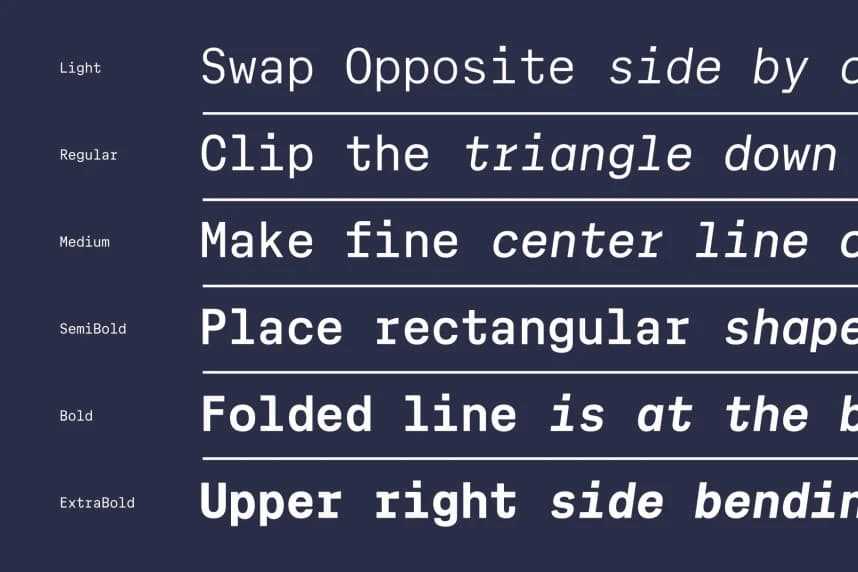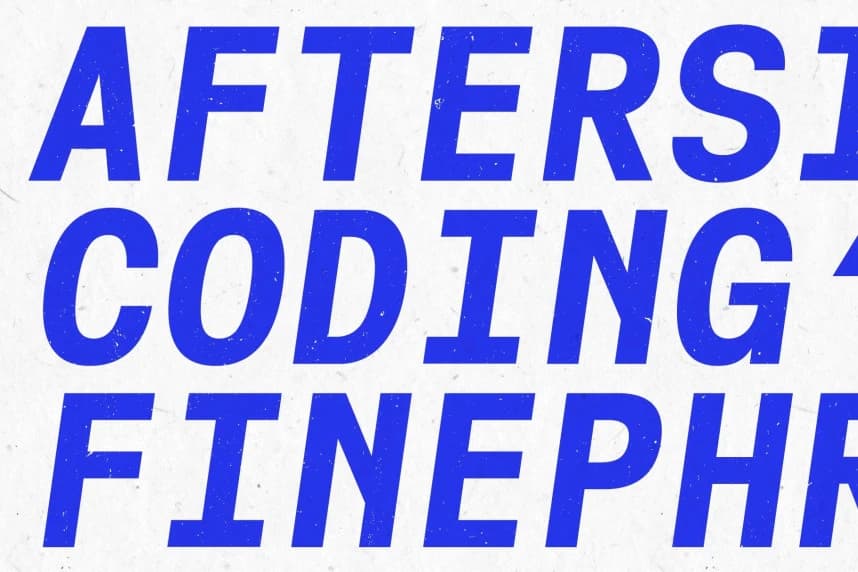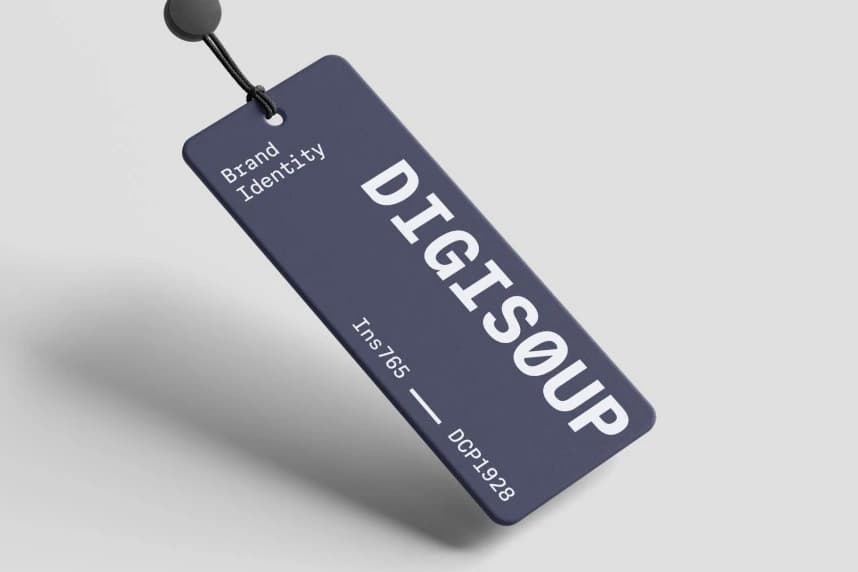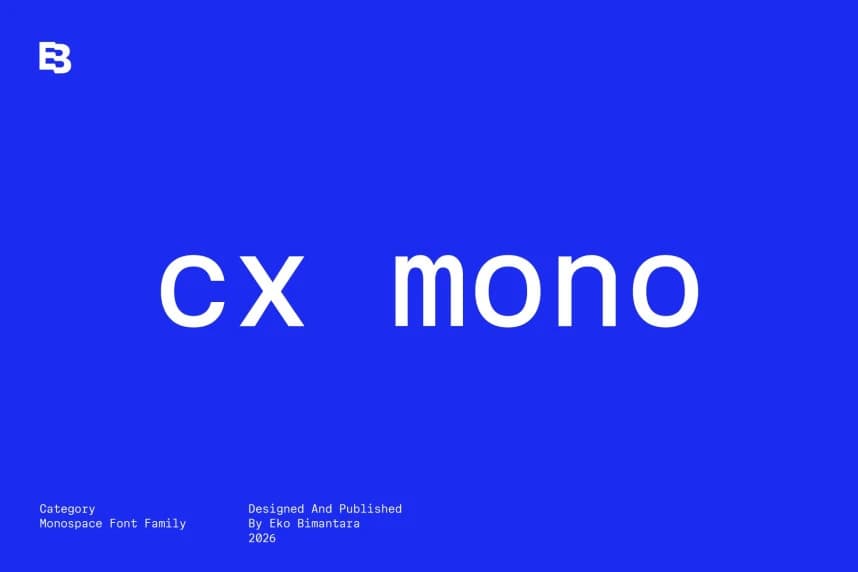
Cx Mono Font Family, netlik, denge ve çağdaş estetiğe yönelik olarak tasarlanmış modern bir sans-serif monospace yazı tipidir. Temiz, modern grotesk sans-serif yapısına sahip olan bu yazı tipi, teknik ve görsel bağlamlarda üstün okunabilirlik sunar.
Cx Mono Font Family, açıklık, denge ve çağdaş estetik için tasarlanmış modern bir sans-serif monospace tipografisidir. Temiz, modern grotesk sans-serif yapısına sahip olan bu font, teknik ve görsel bağlamlarda mükemmel okunabilirlik sağlar.